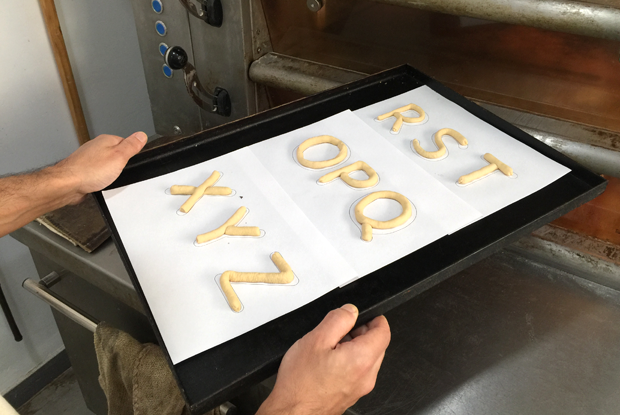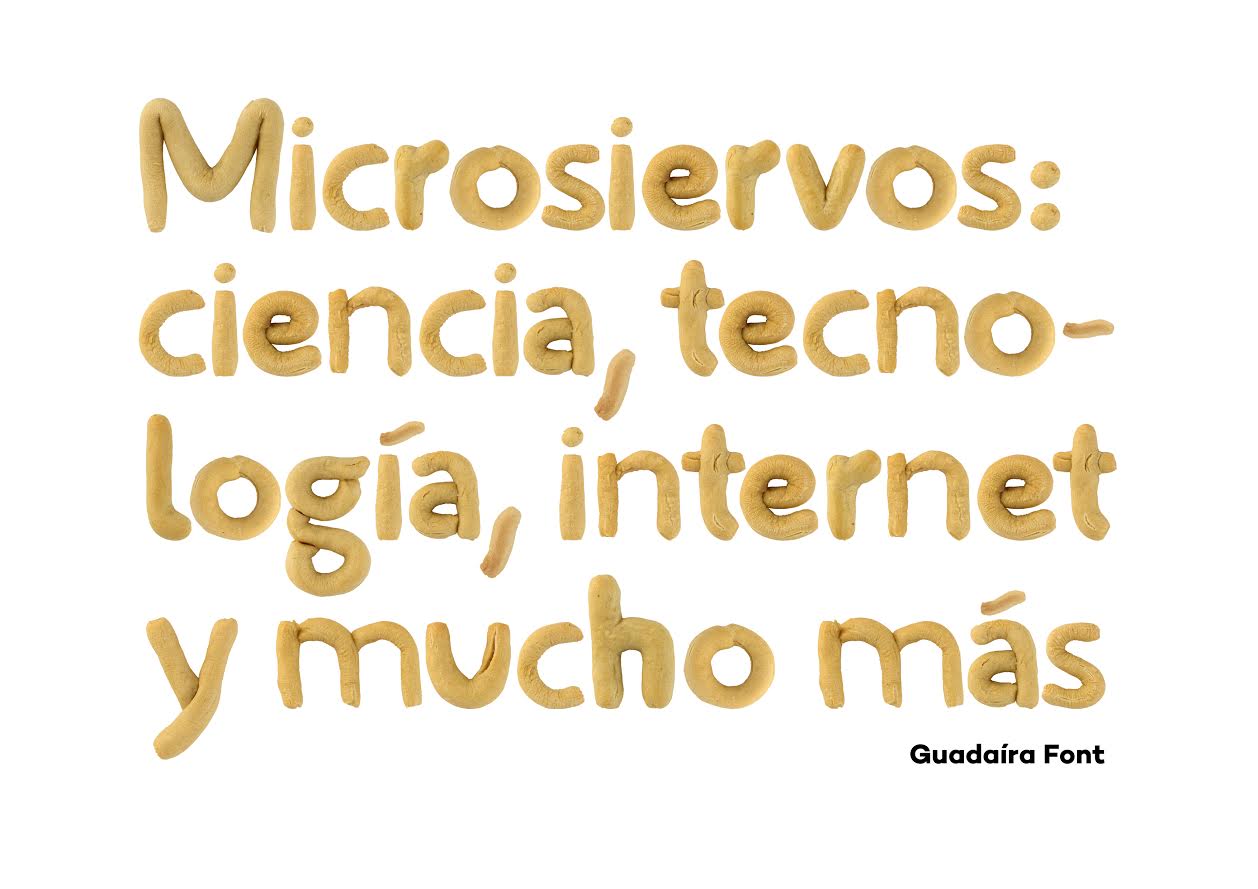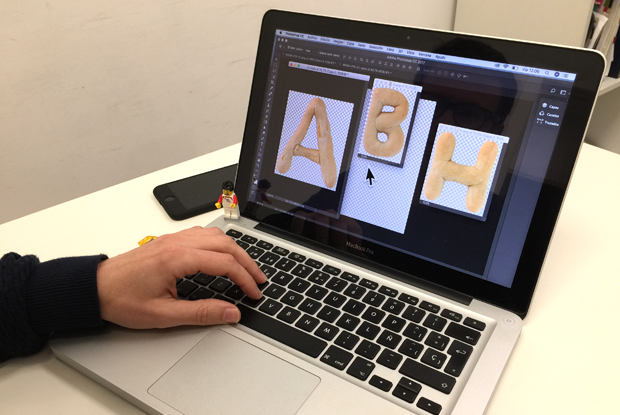
“Recién sacada del horno”, dice Ricardo Vargas del estudio Creativa. Y lo dice en un sentido bastante literal: Guadaíra Font es un tipografía tridimensional hecha a mano con masa de pan, horneada y convertida en una fuente tipográfica con licencia Creative commons. “Es un homenaje a Alcalá de Guadaíra, mi pueblo y el pueblo que gracias a su río, a los molinos y al trabajo artesanal antiguamente surtía de pan a toda la provincia de Sevilla, repartiéndolo en burro y en tren.” Es por eso que durante muchos años Alcalá de Guadaíra era conocida como Alcalá de los Panaderos.
En la web de Creativa se puede ver el “cómo se hizo” Guadaíra Font: el alfabeto completo en mayúsculas y en minúsculas, los números, los signos y los símbolos en una curiosa y hasta fascinante “fusión entre tipografía y gastronomía.”
El resultado es una “tipografía de imágenes”, explica Ricardo. “La tipografía no se instala de forma convencional para usarla en Word, por ejemplo. Es una tipografía de imágenes y por tanto para componer una palabra o una frase hay que utilizar un programa de edición de imágenes como Photoshop o similar”; como una versión digital de aquellas plantillas Letraset que permitían montar textos con un poco de maña y de artesanía. Como hacer pan.
“Me gusta imaginar la conexión entre la 'Guadaía Font' y aquellos burros cargados de pan, o al antiguo tren de Alcalá recorriendo cargado de pan toda la provincia de Sevilla. Me gustaría que la tipografía se usase por todo el mundo”, dice Ricardo.